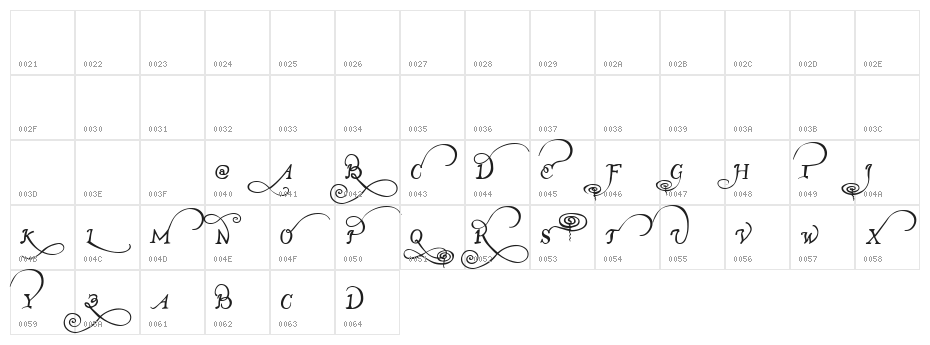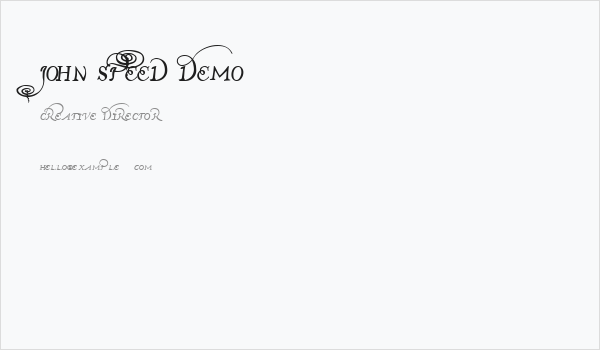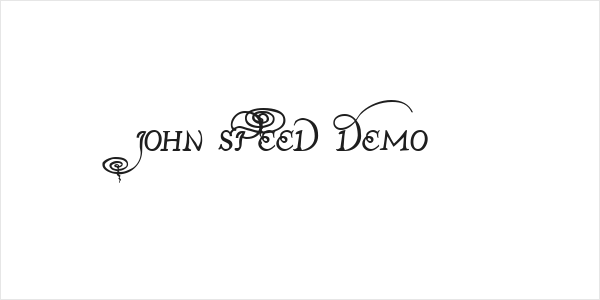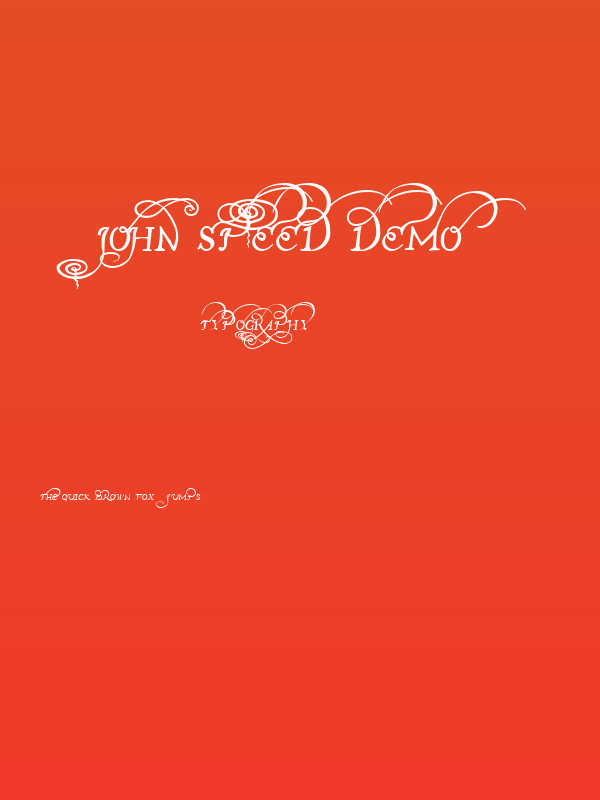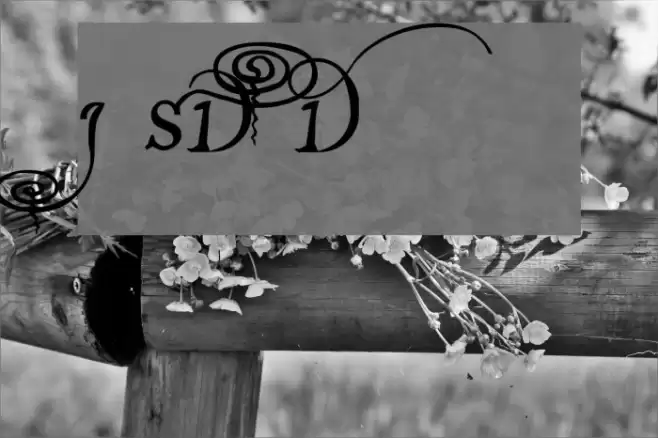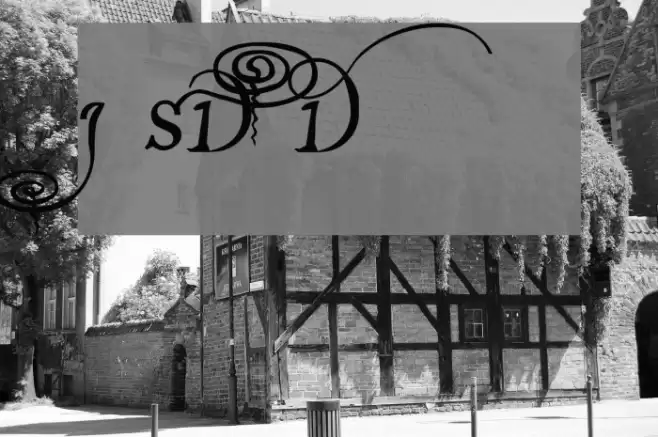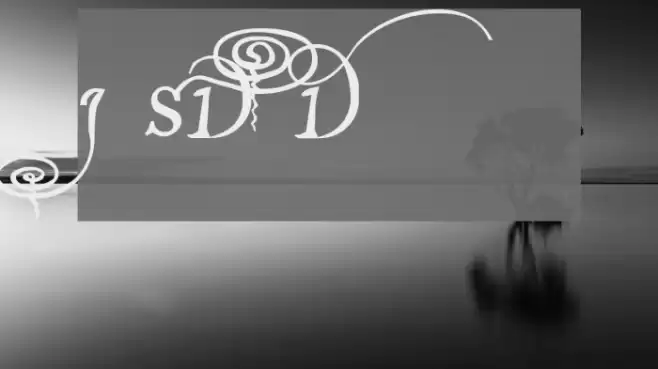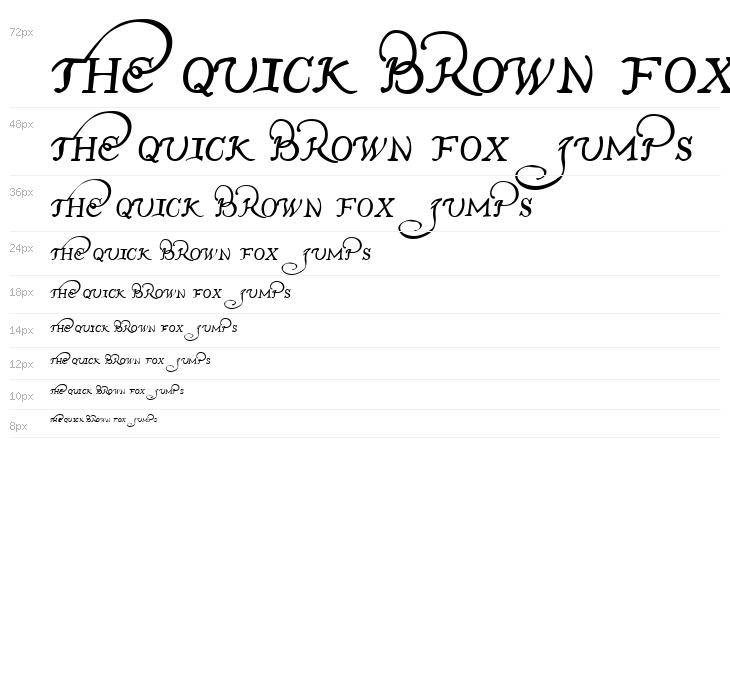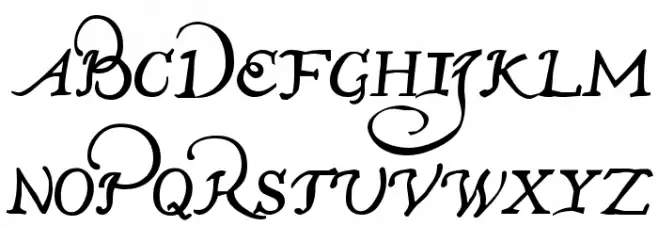
John Speed Demo Font
| Anwendungsfall | Logos, Invitations, Headlines |
| Vorgeschlagene Projekte | Ideal for wedding invitations, luxury branding, and high-end product packaging. |